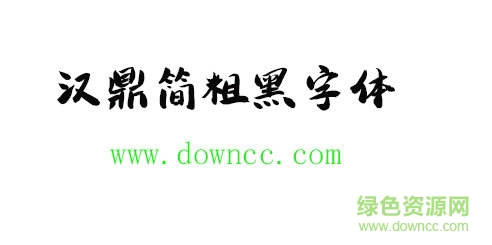
漢鼎簡粗黑字體很適合用于文章或者雜志頭條以達(dá)到醒目的目的,其書寫的方式也非常具有特色,一般只有在特殊的廣告界面才會看得到,雖然應(yīng)用范圍比較廣泛,但是比較少見,有需要的朋友可別錯過了,歡迎登陸綠色資源網(wǎng)下載使用哦。
漢鼎簡粗黑字體別具一格,字跡飄逸灑脫,結(jié)構(gòu)寬松得體,行筆流暢而筆觸凌厲張揚,具有不錯的古風(fēng)韻味,給你的平面設(shè)計、海報設(shè)計、包裝設(shè)計等帶來不錯的藝術(shù)體驗!